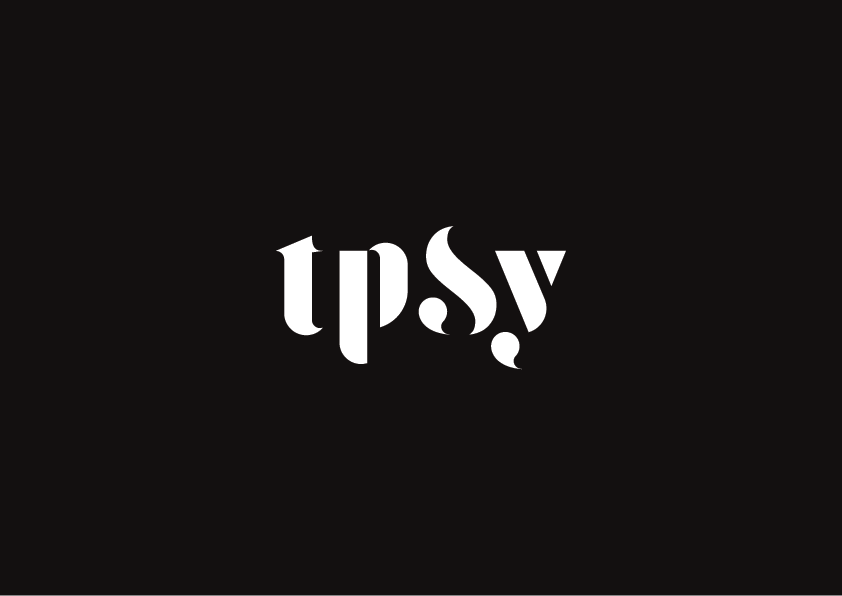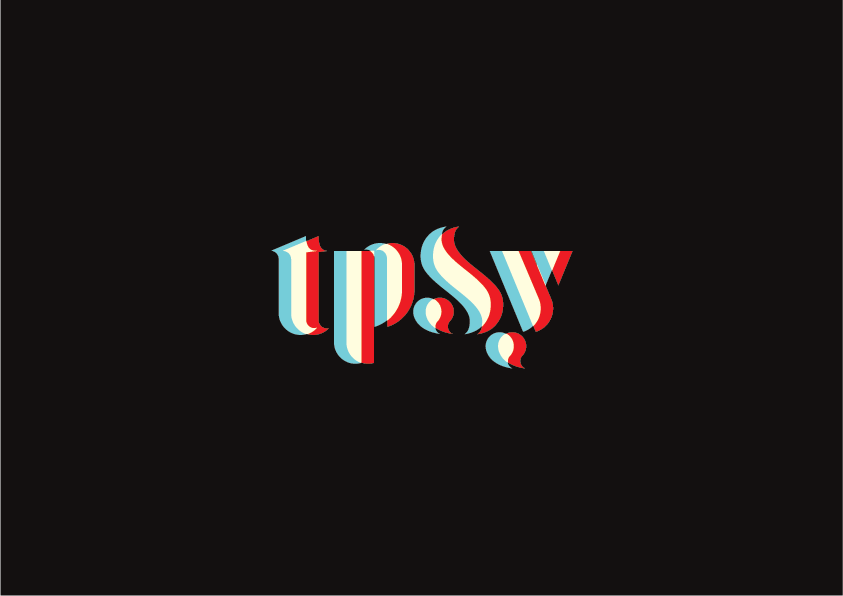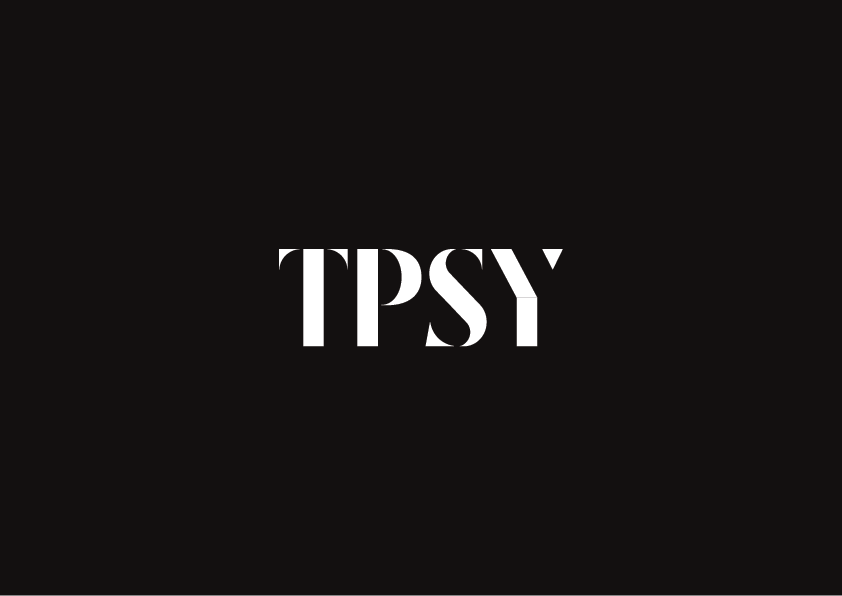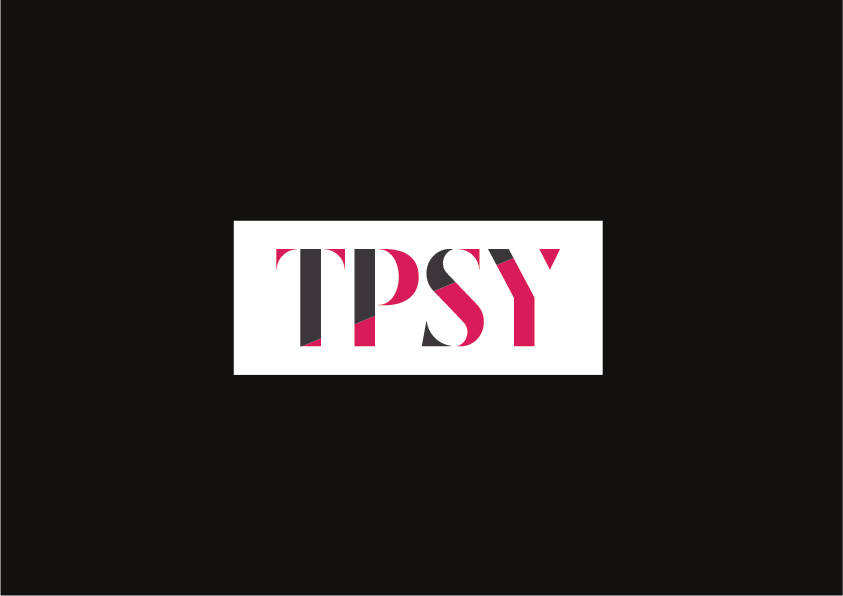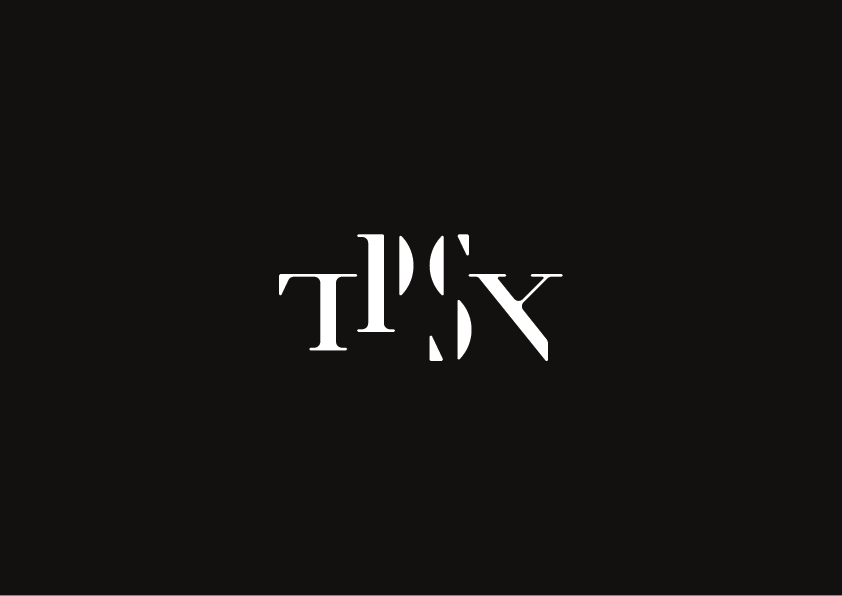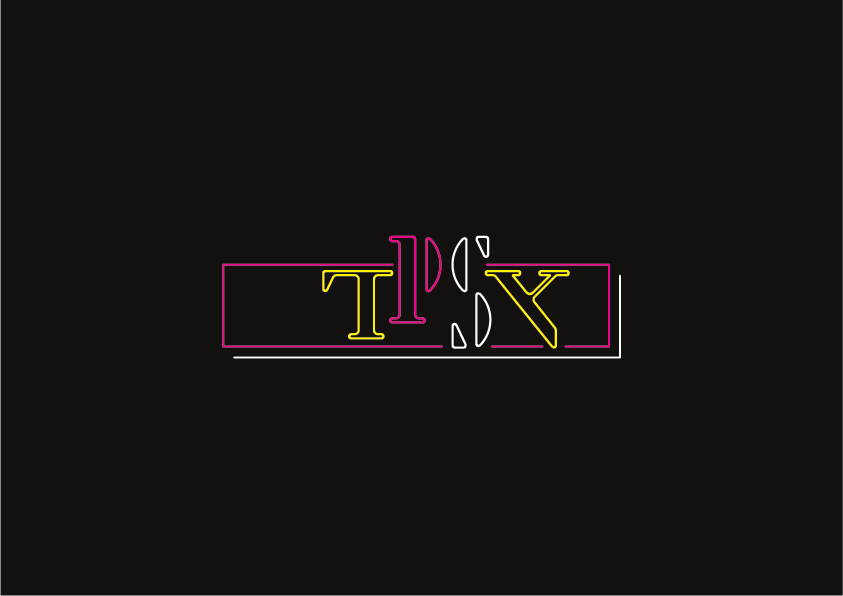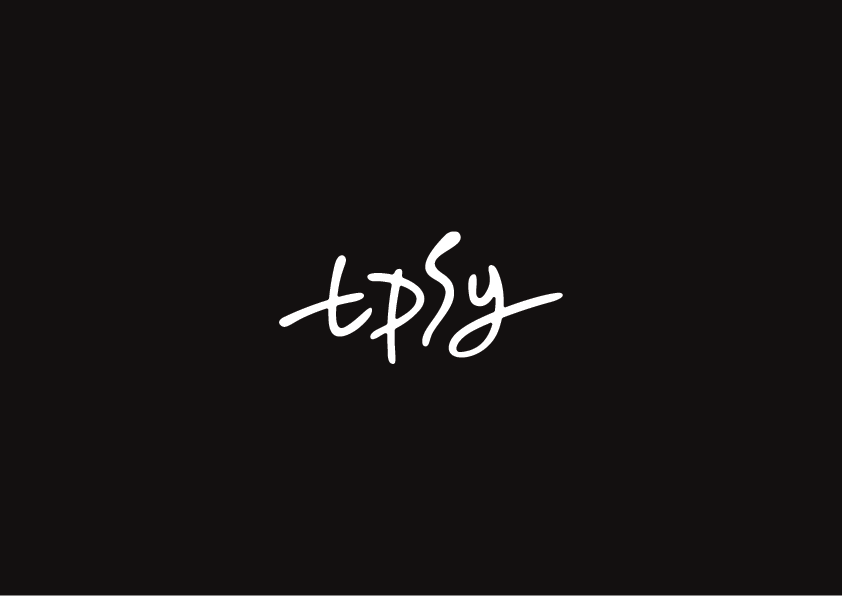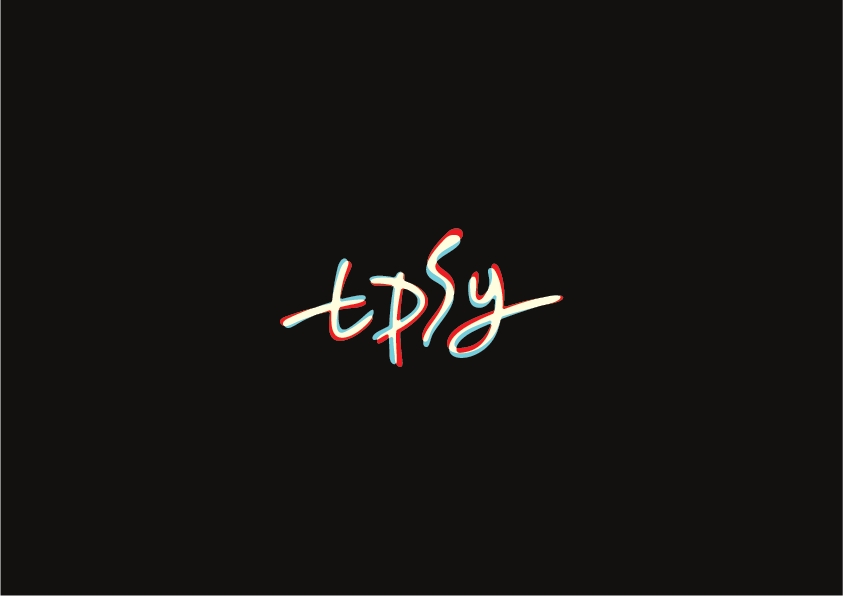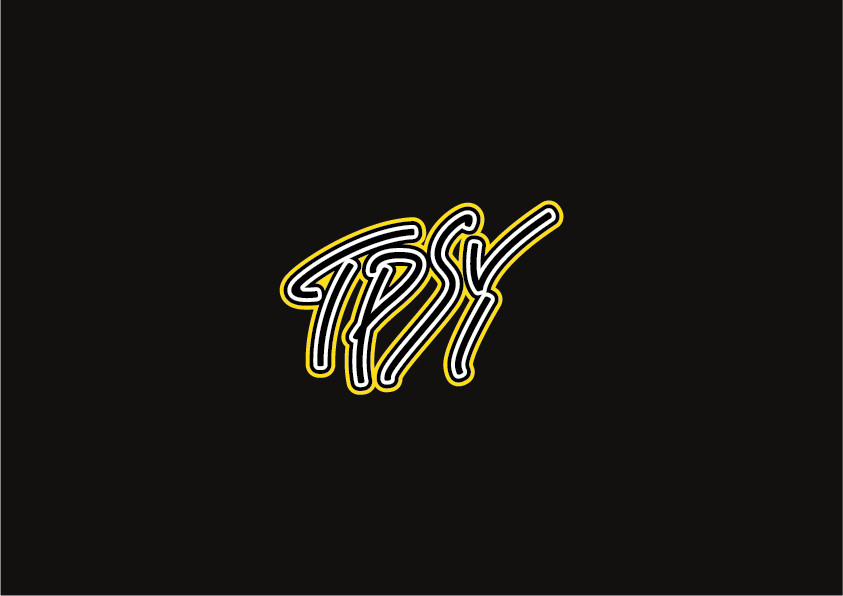
CPNY. 크로스포인트 뉴욕과 진행한 외주작업.
미국에 런칭하는 코스매틱 브랜드 TPSY 팁시의 로고 디자인을 진행했다.
술에 취한 듯 살짝 비틀거리는 느낌. 그러한 컨셉으로 진행한 시안 작업. 코스매틱 제품 패키지 특성상 1도 인쇄를 감안하고 작은 사이즈로 사용될 경우를 고려해야 하는데. 디테일의 밀도를 높이고 싶어도 적정선을 가늠하기가 어려워 시안의 퀄리티가 아쉬웠다. 물론 시간적인 제약도 있었지만. 아직까지는 단기간에 클라이언트의 요구를 파악하고 충족시킬 수 있는 커뮤니케이션 능력이 부족하다. 빠듯한 일정 속에 진행했지만 내가 작업한 시안은 최종적으로 선택되지 못했다.
어렵지만. 아쉽지만. 앞으로 더 열심히 하는 수 밖에.